「お菓子」にぴったりの日本語フリーフォント
今回は、「お菓子」の世界観にぴったりな日本語フリーフォントをご紹介します。
ふわっと甘くて、見た目も可愛らしいお菓子たち。そのやさしい雰囲気やワクワク感を表現するには、フォント選びがとても大切です。まるみのある文字やポップなデザイン、ちょっとレトロで懐かしいタッチなど、お菓子と相性抜群なフォントは、ロゴやパッケージ、ショップのPOPなどに大活躍します。
今回は、スイーツのようにキュートで、見るだけで心がときめく日本語フリーフォントを厳選しました。お菓子の魅力をもっと引き立てるデザインに、ぜひ取り入れてみてください。
お菓子の世界にぴったり!甘くてスイーツな日本語フリーフォント
以下のサンプルのように見ているだけでも美味しそうなフリーフォントをご紹介します!
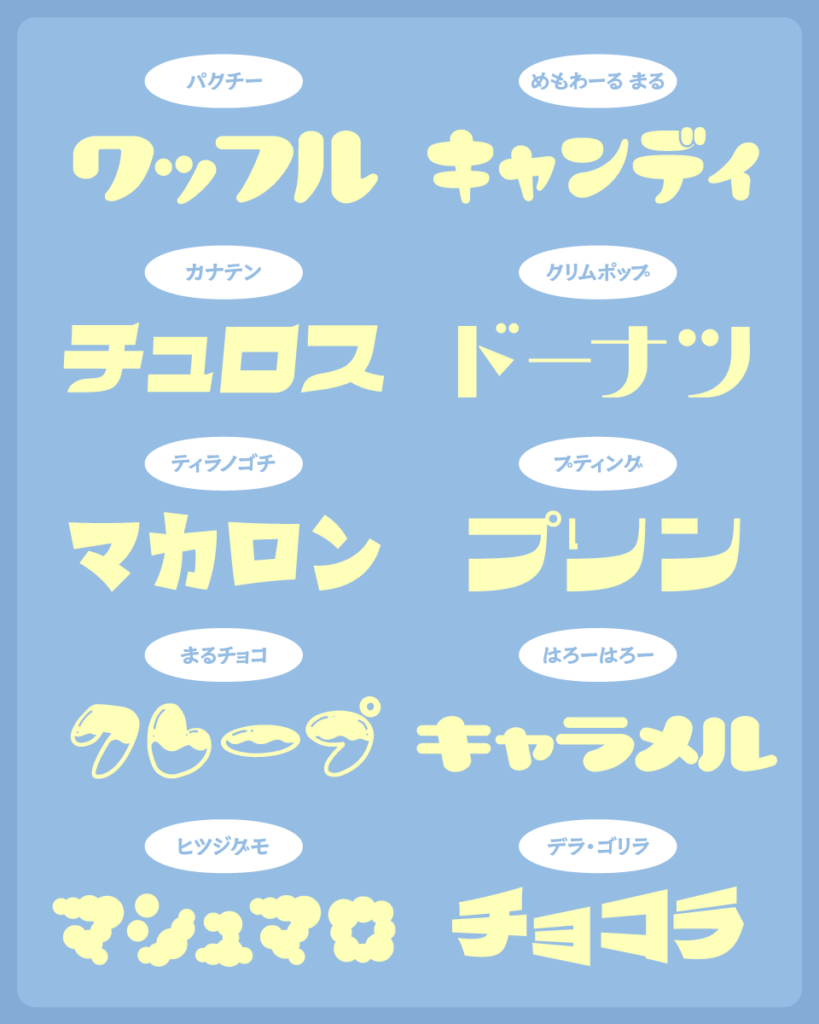
以下よりフォントを紹介します。
クリムポップフォント
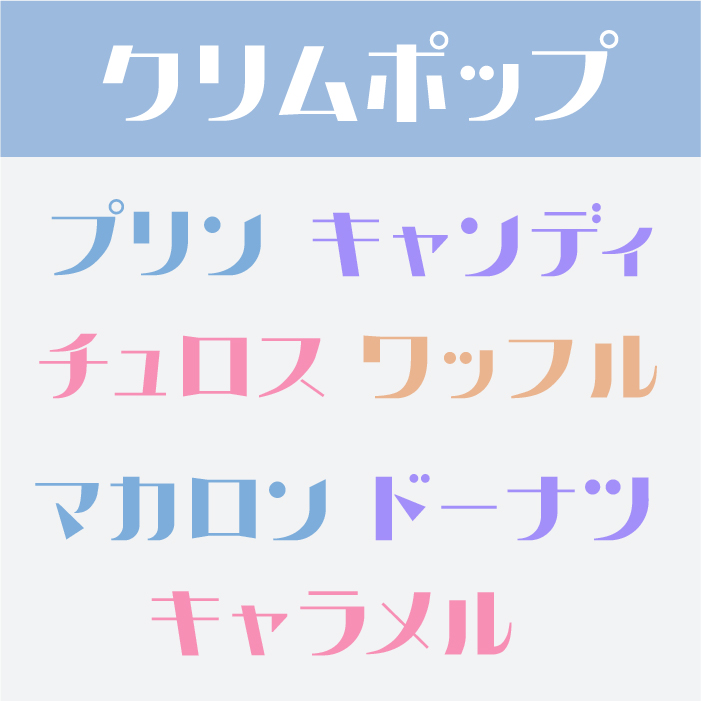
クリムポップフォントは、スッと伸びた直線と丸みを持つ字形が、やさしさとモダンさを同時に感じさせる、ポップで洗練された印象のフォントです。
プティングフォント
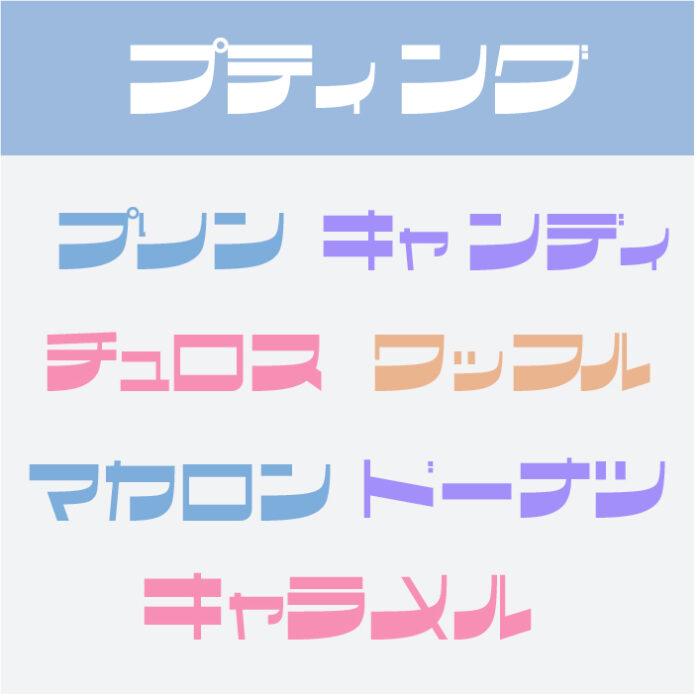
プティングフォントは、ゆるやかなカーブとぷっくりしたボリューム感が特徴で、見ているだけで甘さが伝わるような、スイーツ感満載のフォントです。
デラ・ゴリラフォント
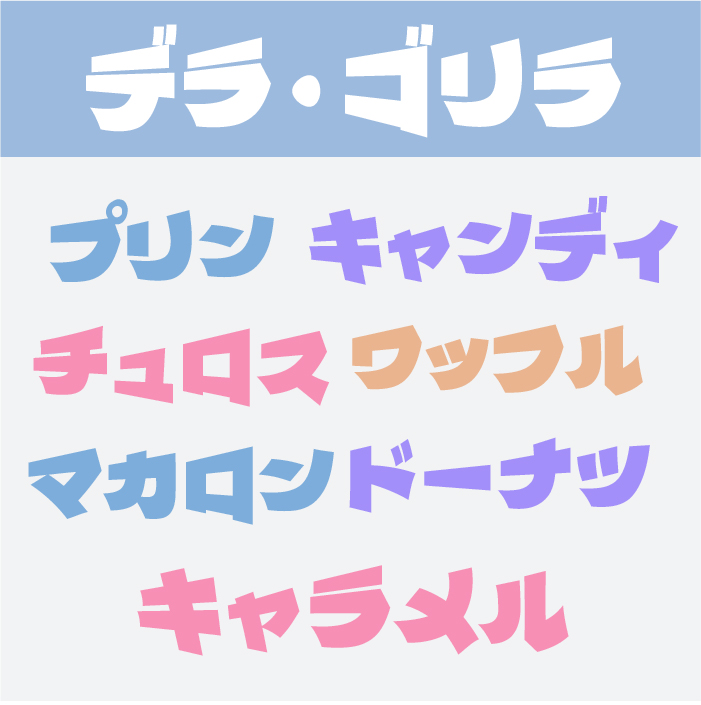
デラ・ゴリラフォントは、どっしりとした太めのシルエットとユーモラスなバランスがクセになる、見た目のインパクトが強くロゴにしても目を引く楽しいフォントです。以外とスイーツ系にもハマるフォントです。
ニクキュウフォント
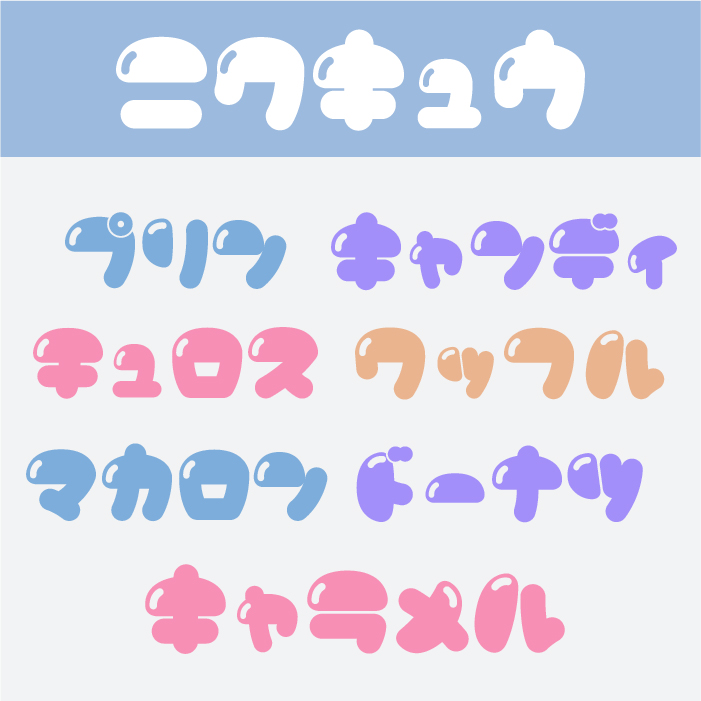
ニクキュウフォントは、ぷにっとした質感と、つやのあるようなハイライトが特徴で、まるでゼリーやグミのような食感を思わせる愛らしいフォントです。
びーんずフォント
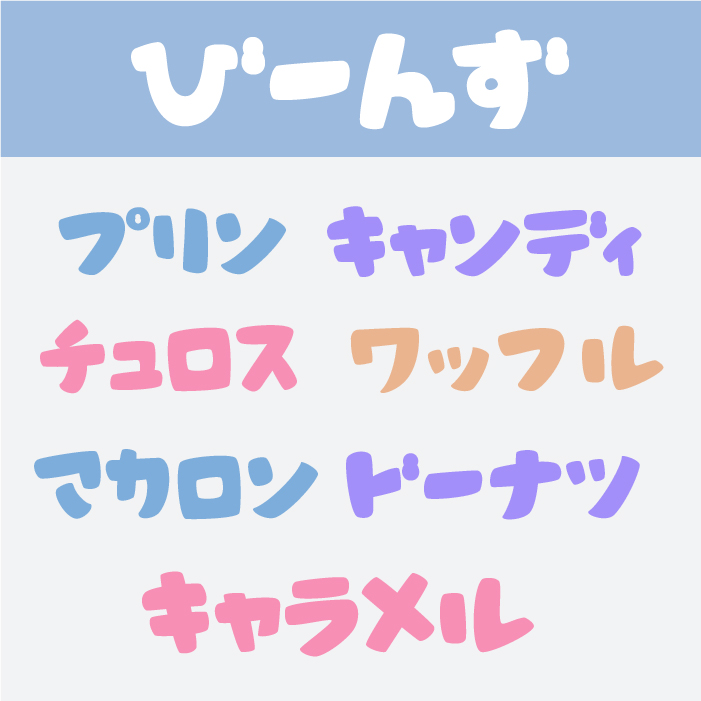
びーんずフォントは、ゆるやかな動きと柔らかい輪郭で、ピーナッツなどの豆菓子のような素朴な甘さを表現している、ほっとする雰囲気のフォントです。
ヒツジグモフォント
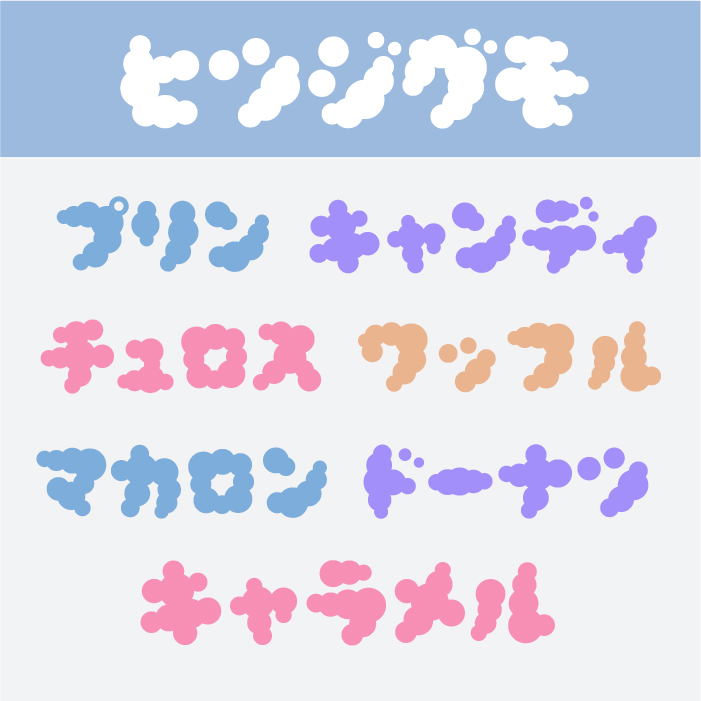
ヒツジグモフォントは、もくもくとした形状が印象的で、綿菓子やマシュマロを連想させる、ふんわりと優しく包み込むようなフォントです。
はろーはろー
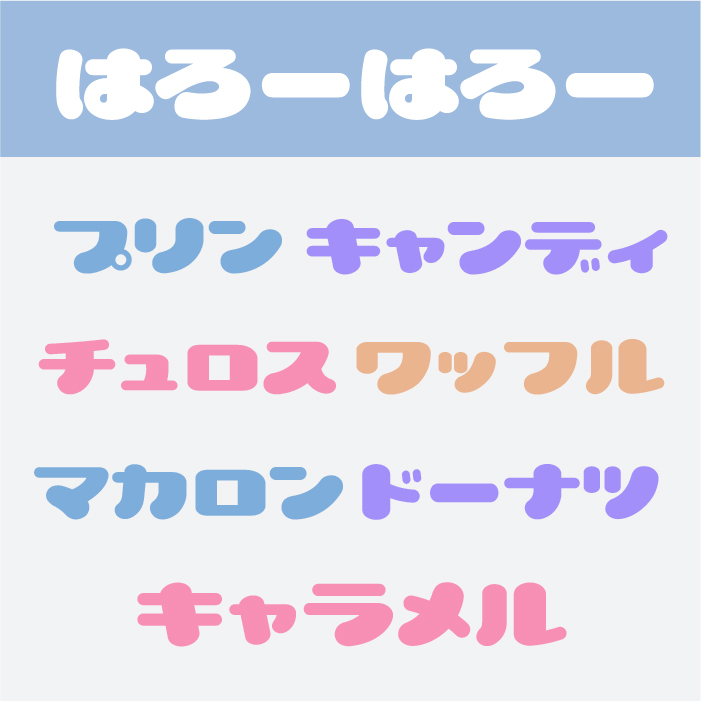
はろーはろーフォントは、ころんとした形がかわいらしく、どこか懐かしさもある丸みで、日常の小さな甘さをやさしく伝えるフォントです。
まるチョコフォント
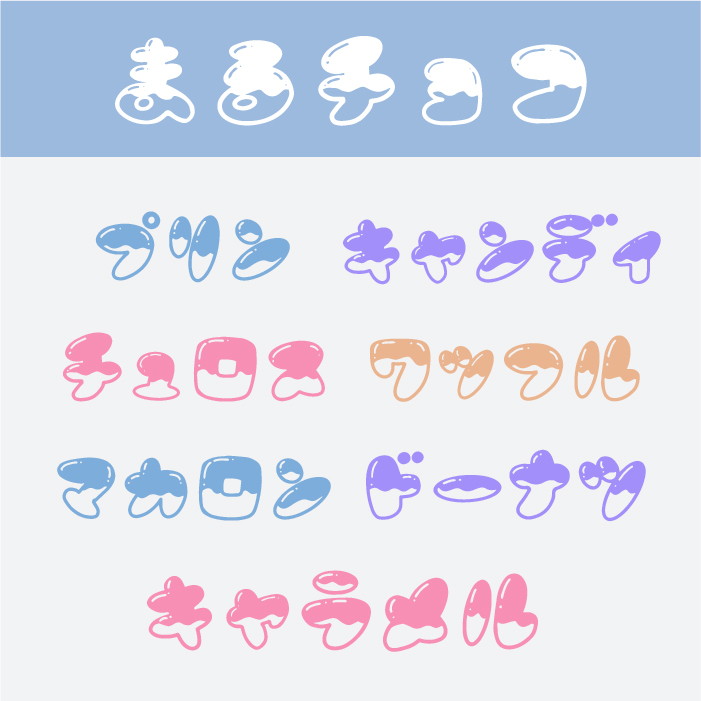
まるチョコフォントは、溶けかけのチョコレートのようなとろみと、ひとくせある形状が、見た目にも楽しいデコレーション感のあるフォントです。
ティラノゴチフォント
ティラノゴチフォントは、かっちりとしながらも丸みを帯びた字形が、しっかり甘い焼き菓子のような重厚感と親しみやすさを兼ね備えたフォントです。
カナテンフォント
カナテンフォントは、すっきりとした曲線と適度な太さで、チョコやキャラメルのようなとろける滑らかさが感じられる上品なフォントです。
めもわーる-まる
めもわーるフォントは、やわらかな手書き風の曲線と、ぽってりと丸みのある造形が特徴のフォントです。幼さを感じさせるフォルムで、まるで幼児向けお菓子のパッケージに使われていそうな可愛らしさを持っています。
パクチー
パクチーフォントは、太めの線とゆるやかな丸みにより、もちもちした見た目が印象的なフォントです。子ども向けのお菓子やキャラクター商品とも相性が良く、親しみやすさを演出できるフォントです。